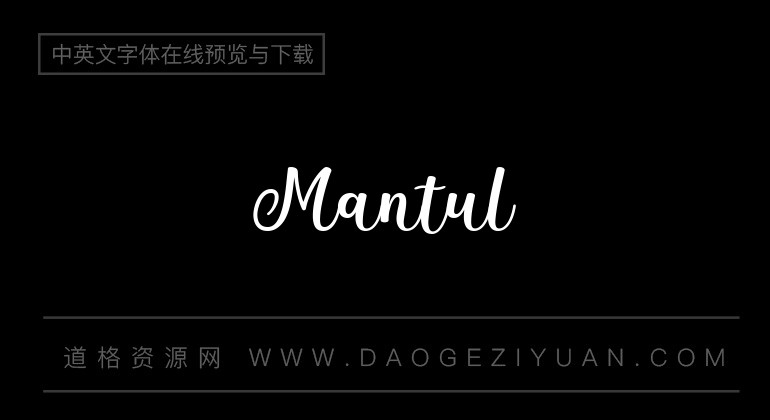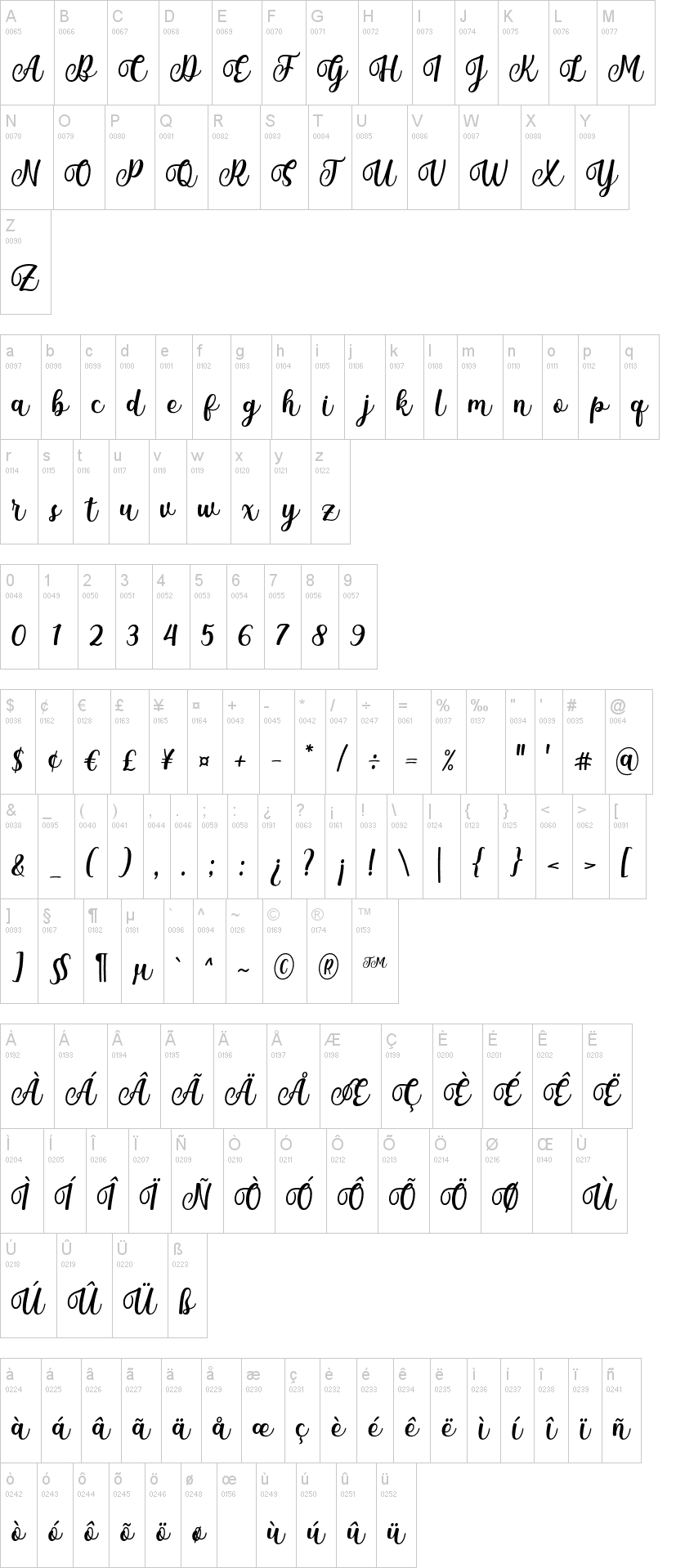
Mantul
Mantul 字体是一款源自印尼的漂亮的书法字体,它是一种粗犷、古朴的书法风格,具有明显的自然形状和独特的细节。它的字符拥有柔和的线条,有助于提升文字的美感,使文字充满活力,更具有视觉效果。Mantul 字体的特点是有力的笔画,结构紧凑,让文字更加清晰,更易于阅读。它可以用于商业广告、设计、印刷和网络媒体等多个领域,能够为设计师的作品增添一份独特的魅力。
Mantul是一款非常不错的手写艺术字体,具有很好的视觉感,适合于文化类的宣传设计、商业类品牌的广告和产品包装设计以及个性化文字排版等较多场景。
Mantul字符映射图